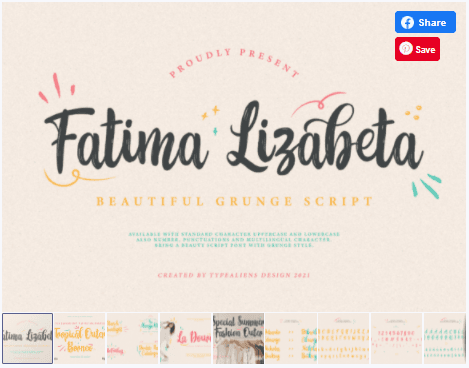
Fatima Lizabeta Font
Fatima Lizabeta — изящный, элегантный и плавный рукописный шрифт. У него красивые и хорошо сбалансированные персонажи, и в результате он подходит для широкого круга дизайнов. Добавьте его к своим самым креативным идеям и обратите внимание, как он оживляет их!